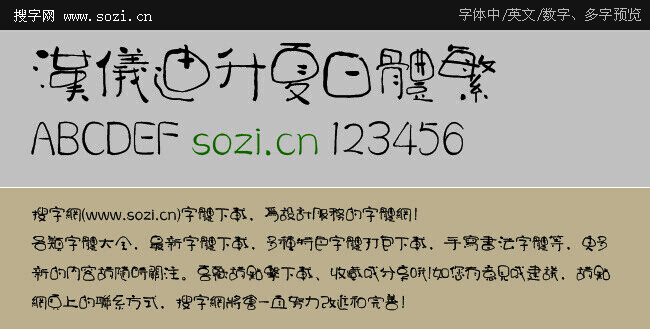
漢儀迪升夏日體繁
搜字網(wǎng)給大家提供一款漢儀迪升夏日體繁中文字體下載,漢儀迪升夏日體是一套兒童卡通風格的POP字體,該字體線條圓潤,轉角以曲線處理,粗細搭配合理,看上去非?蓯,整體效果非常出色。適用于畫冊設計、海報設計、包裝設計等場合使用。(本字體為個人非商用版,如需要商用請聯(lián)系漢儀公司購買版權)